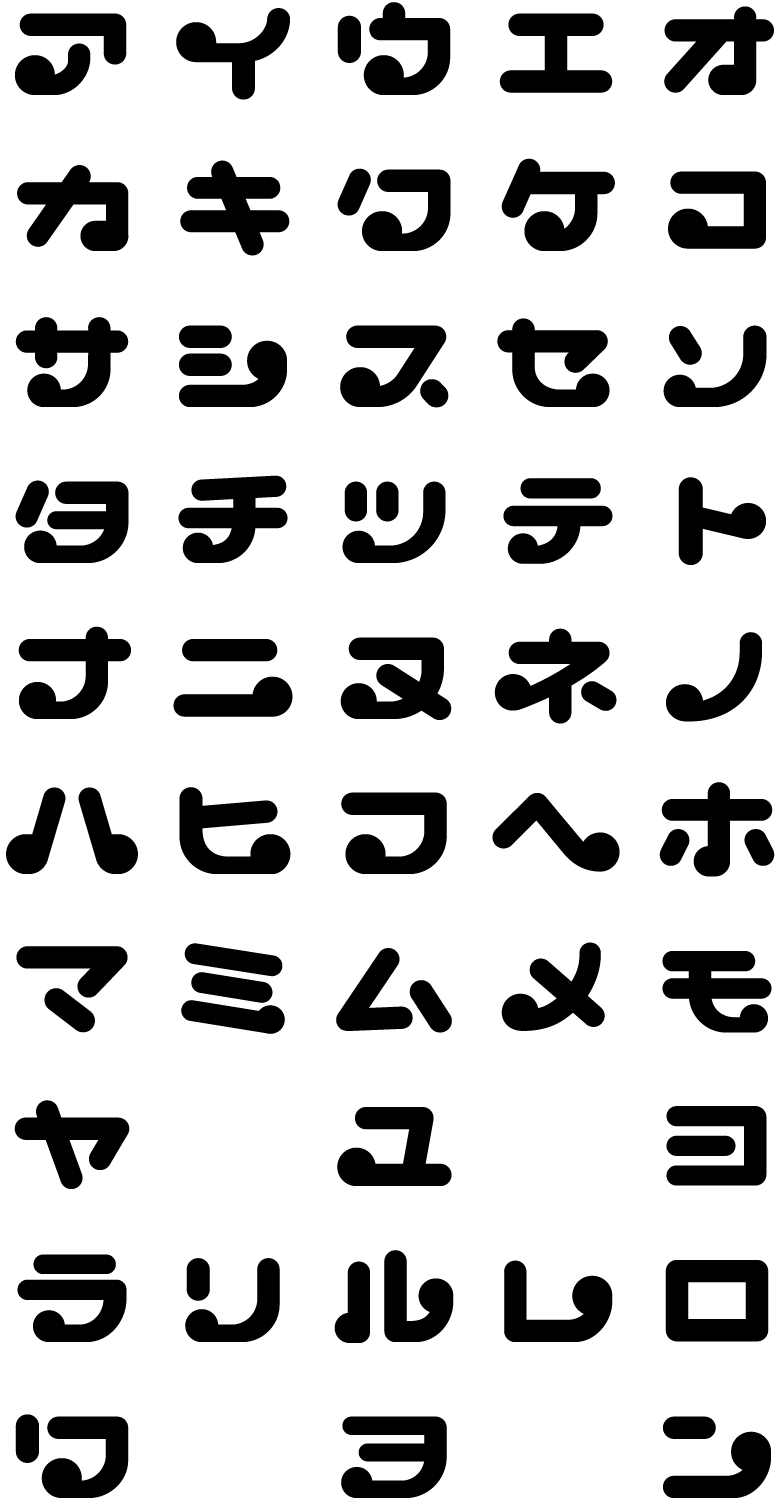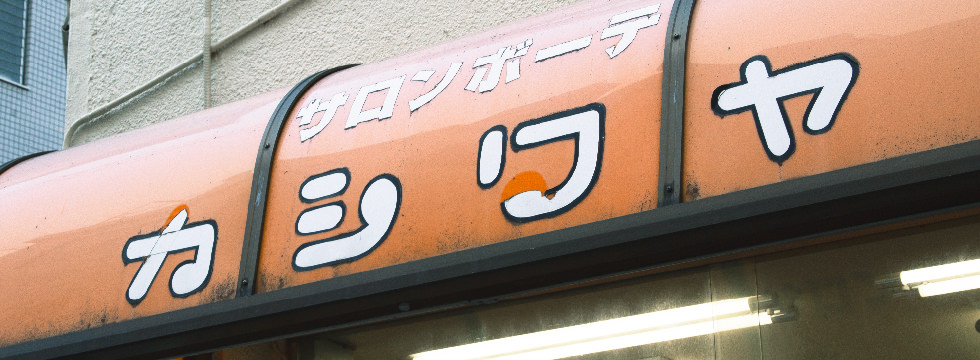
ところどころ欠けており、年月を感じる味わいが漂う。丸ゴシックをベースにくるんとした丸いかざりがやさしさを感じさせる。
「カシワヤ」はオリンピックの年の1962年に日暮里で開業した美容室だ。もともとは浅草にあった「カシワヤ」から高橋さんが独立し、屋号をのれんわけした形となる。現在でも残っている看板の文字は40年ほど前に当時の従業員のみなさんでスケッチし、そこから看板屋さんに発注してできたそうだ。「仕事柄ね、かわいく柔らかくいきたい。みんなの憩いの場所としながら綺麗になる、美しくなる場所と思っています。」そんなお店の雰囲気を体現したような、くるんとしたかわいい看板文字である。
“Kashiwaya” is a hair salon that opened in Nippori, Tokyo in 1962, the year of the Tokyo Olympics. “Kashiwaya” was originally established in Asakusa, and Ms. Takahashi was given that name and split the brand. The letters on the signboard which still remains today were sketched by its employees at that time about 40 years ago, and ordered it the signboard maker. “I want the letters to be cute and gentle because here is a place where everyone can relax while also being beautiful,” The cute, rounded letters on the sign embody the atmosphere of her shop.